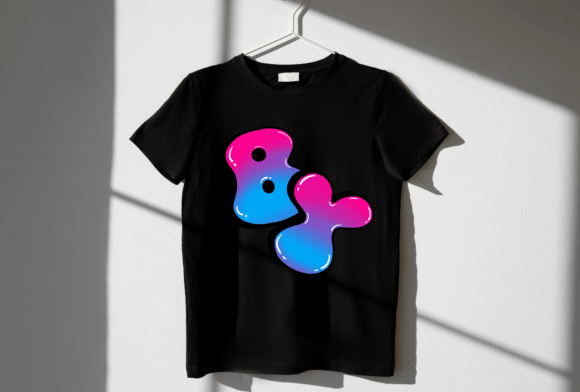
Lovely Graffiti Font
Lovely Graffiti Font – خط جرافيتي أنيق ومميز
أضف لمسة من الإبداع والجرأة إلى تصاميمك مع Lovely Graffiti Font، الخط المثالي لعشاق الفن الحضري والجرافيتي الأنيق. يتميز هذا الخط بتصميم فني نابض بالحياة، يجمع بين العفوية والأسلوب العصري، مما يجعله خيارًا مثاليًا للمشاريع الإبداعية مثل:
✔ الشعارات والبراندينغ
✔ تصاميم التيشيرت والملابس
✔ أغلفة الألبومات والبوسترات
✔ محتوى السوشيال ميديا والإعلانات
✔ تصاميم الجرافيك والفن الرقمي